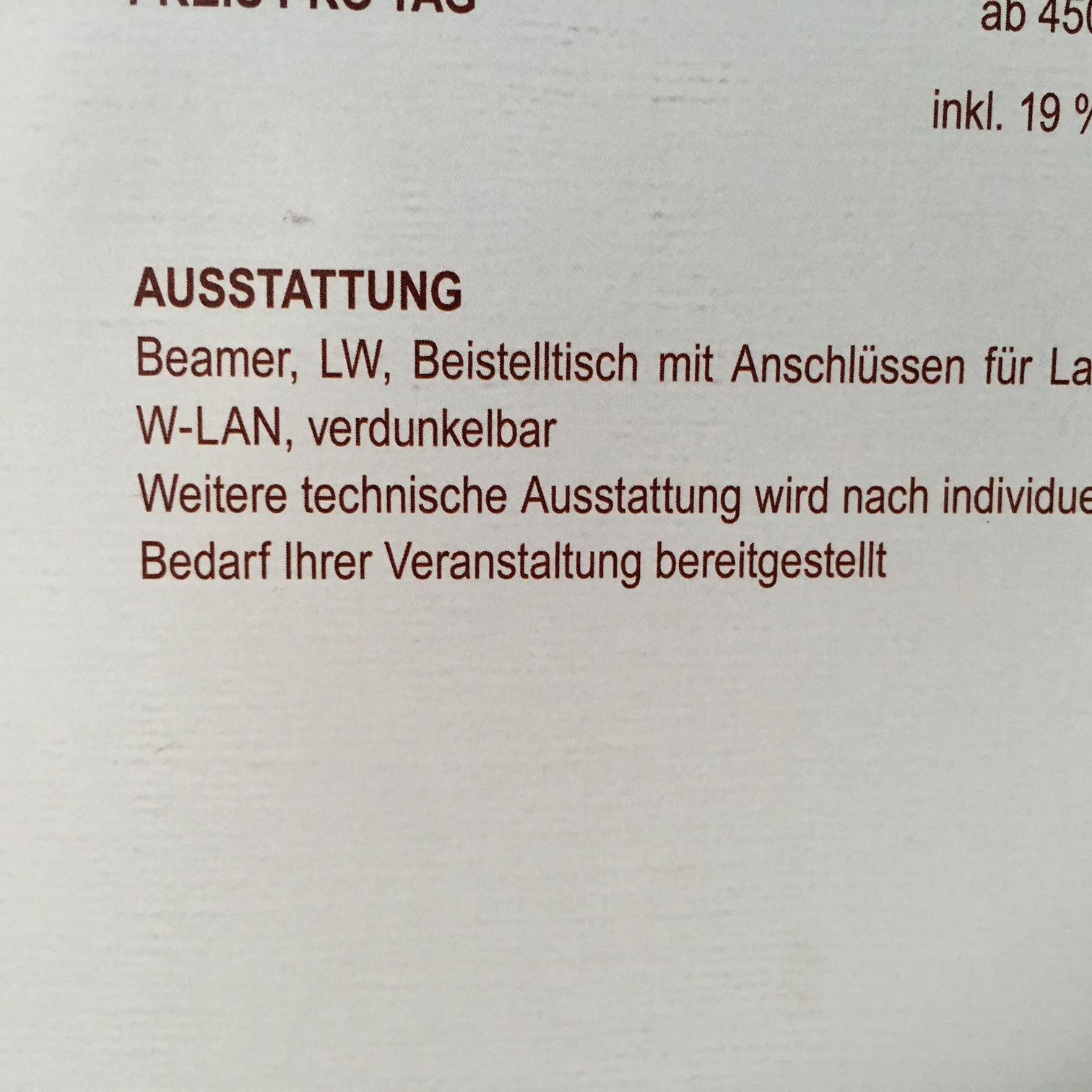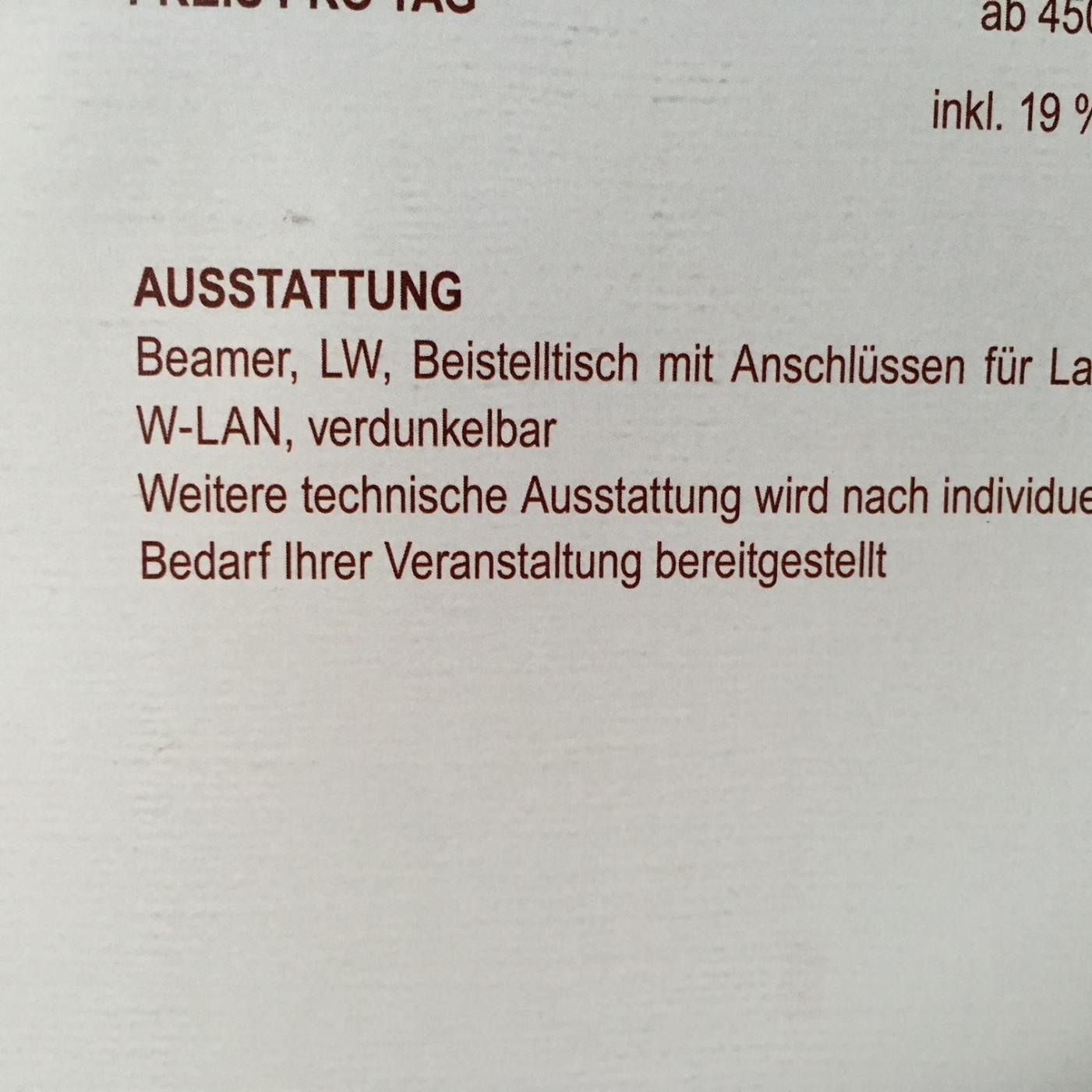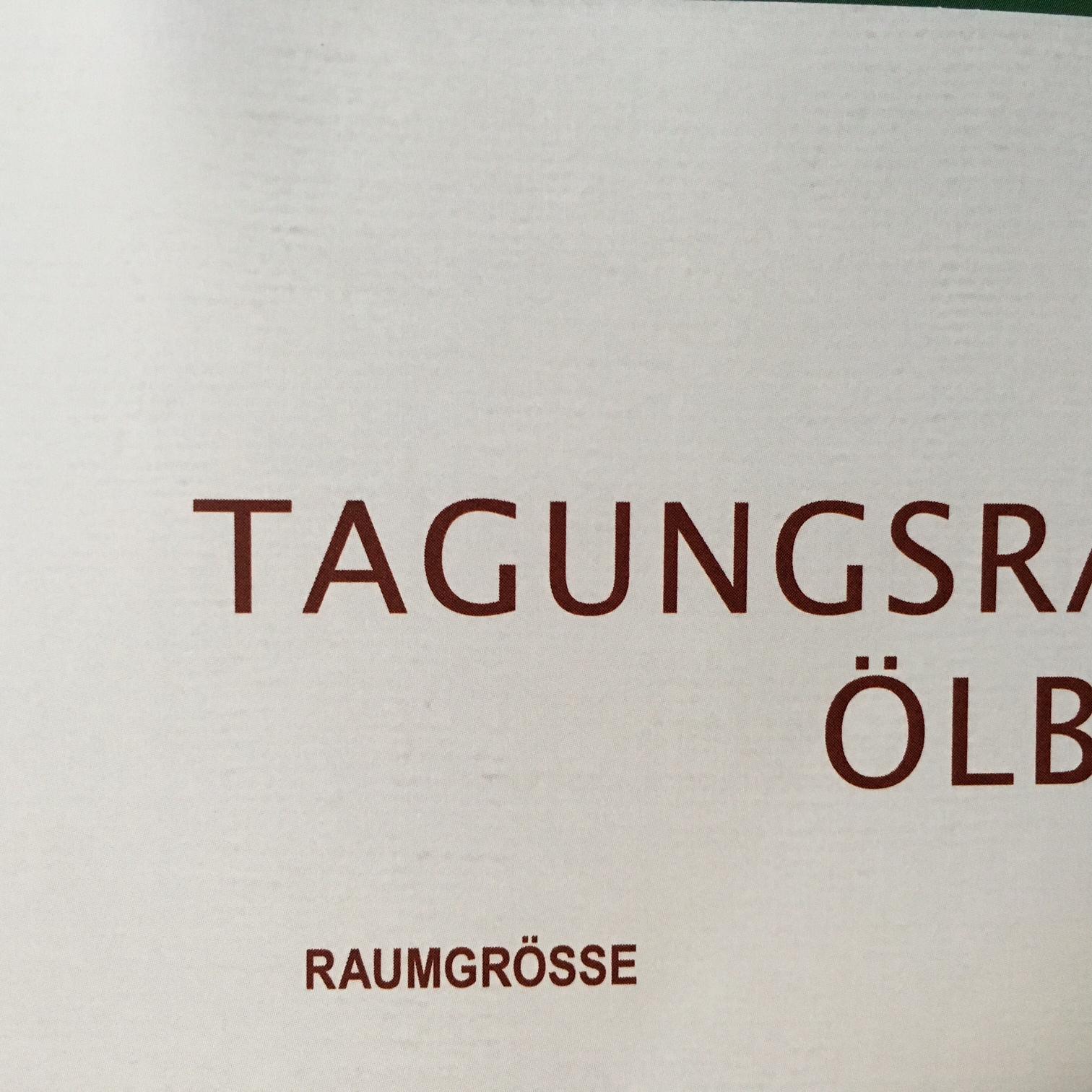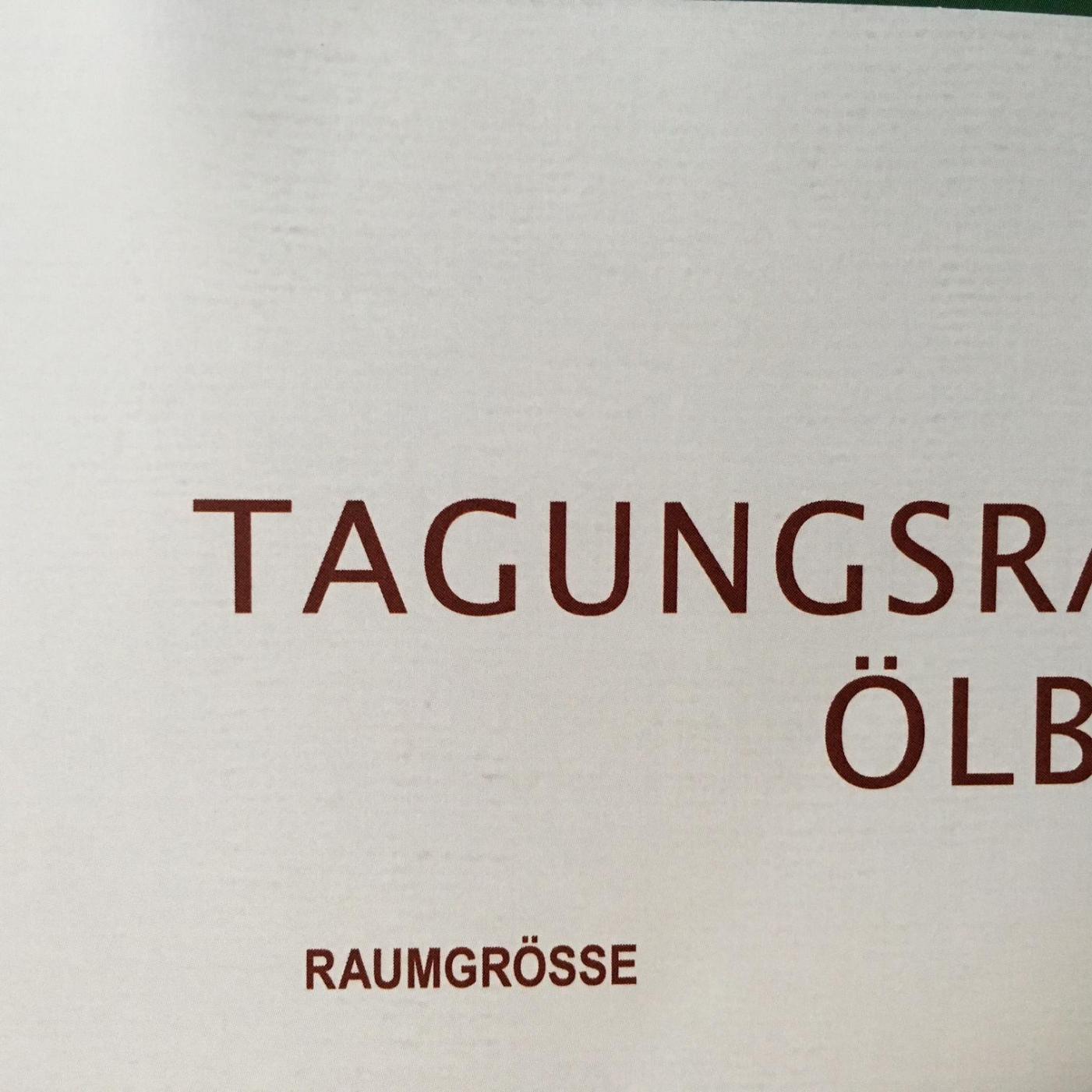
Welche Schriften sind das (Headline / Fließtext)?
Guten Morgen, weiß jemand um welche Schriften es sich handelt. Einmal Headline, einmal Fließtext Schrift. Bei der Headline vermute ich die Lato. Bei Fließtext wahrscheinlich auch irgendwas standardmäßiges. Weiß jemand weiter?
Also die Lato isses schon mal nicht. Die sieht so aus:
Beim Fließtext würde ich mal auf Arial Narrow tippen.
Lucida Sans, Luxi Sans von B & H?
Die wurde Anfang des Jahrtausends oder um die Jahrtausendwende sehr populär und breit gestreut. Die Lucida wurde von MS verbreitet und die Luxi war in einigen Office-Paketen anderer Hersteller drinnen?
Lucida Sans auf MS-Typography:
Lucida Sans Regular Einzelheiten: